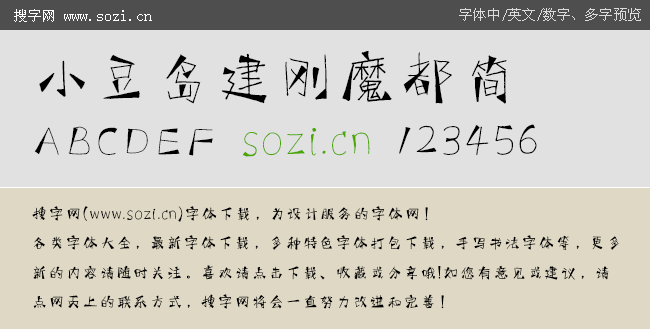
小豆島建剛魔都簡(jiǎn)
搜字網(wǎng)提供一款小豆島建剛魔都簡(jiǎn)中文字體下載,小豆島建剛魔都簡(jiǎn)體是一款風(fēng)格偏硬的藝術(shù)字體。字形夸張變形,趣味十足。適合應(yīng)用于海報(bào)設(shè)計(jì)、POP設(shè)計(jì)、兒童產(chǎn)品包裝設(shè)計(jì)等應(yīng)用。